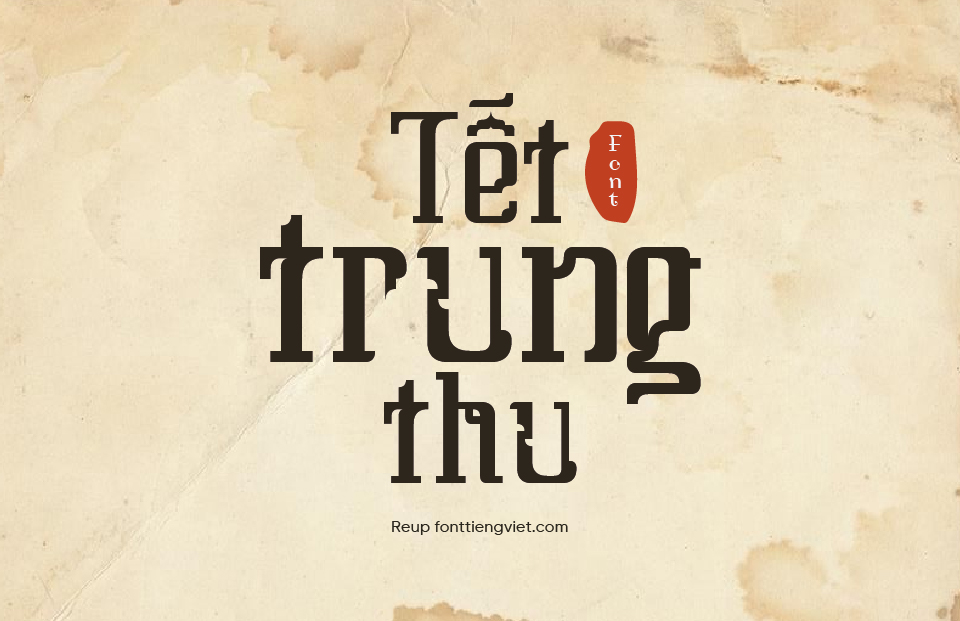
Khi nhắc đến các dự án thiết kế mùa Tết Thiếu nhi và rằm tháng Tám, việc đa dạng hóa thư viện phông chữ là điều vô cùng cần thiết. Font Việt hóa LNTH Daybreaker mang đến một nguồn năng lượng mới mẻ, rực rỡ, trở thành một font trung thu đầy tiềm năng cho những ấn phẩm đòi hỏi sự phá cách mà vẫn giữ trọn vẹn không khí nhộn nhịp của lễ hội.
Dấu Ấn Khác Biệt Của LNTH Daybreaker
Đúng như tên gọi “Daybreaker” (tượng trưng cho ánh rạng đông bứt phá), phông chữ này sở hữu đường nét dứt khoát, hiện đại nhưng vẫn được chấm phá bởi những nét uốn lượn khéo léo. Khi ứng dụng vào thiết kế, nó gợi lên sự sôi động, rực rỡ của những đêm rước đèn hay tiếng trống múa lân rộn rã.
• Thiết kế cân bằng: Sự hòa quyện giữa độ dày dặn của chữ và nét cọ linh hoạt giúp tiêu đề nổi bật một cách mạnh mẽ.
• Việt hóa chỉn chu: Các dấu câu tiếng Việt được căn chỉnh khoảng cách (kerning) tỉ mỉ, giúp nội dung liền mạch và tối ưu hiển thị trên mọi nền tảng.
• Độ linh hoạt cao: Rất dễ dàng để áp dụng các hiệu ứng chữ (stroke, drop shadow, glow) mà không làm mất đi form dáng chuẩn của từng ký tự.
Giải Pháp Typography Tối Ưu Cho Mùa Lễ Hội
Với đặc tính trực quan mạnh, font việt hóa LNTH Daybreaker là “trợ thủ” đắc lực để gia tăng sự chú ý của người xem, đặc biệt phù hợp cho:
• Thiết kế Banner, Landing Page cho các chiến dịch flash sale hoặc sự kiện Trung Thu.
• Typography nổi bật trên các ấn phẩm video ngắn giới thiệu sự kiện hoặc review hộp bánh Trung Thu.
• Bao bì sản phẩm hướng tới tệp khách hàng trẻ trung, yêu thích sự năng động và hiện đại.
• Thiết kế menu, standee cho các quán cafe, nhà hàng chạy chương trình check-in mùa trăng rằm.
Việc bổ sung Font Việt hóa LNTH Daybreaker vào bộ sưu tập typography sẽ mở ra nhiều hướng sáng tạo mới mẻ. Đây là một phông chữ không chỉ đẹp về mặt thẩm mỹ mà còn cực kỳ hiệu quả trong việc tạo điểm nhấn thị giác, giúp tác phẩm của bạn thực sự “tỏa sáng” trong dịp lễ này.